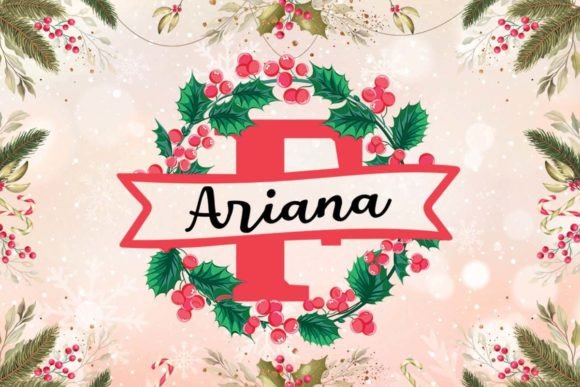
FREE Merry Christmas, Christmas Font
FREE Merry Christmas, Christmas Fontのような高品質の素材をお探しの場合、このプレミアムパッケージはクリエイティブなプロジェクトに素晴らしい選択です。
POD(オンデマンド印刷)製品、結婚式の招待状、またはソーシャルメディアのグラフィックを作成している場合でも、FREE Merry Christmas, Christmas Fontは理想的です。